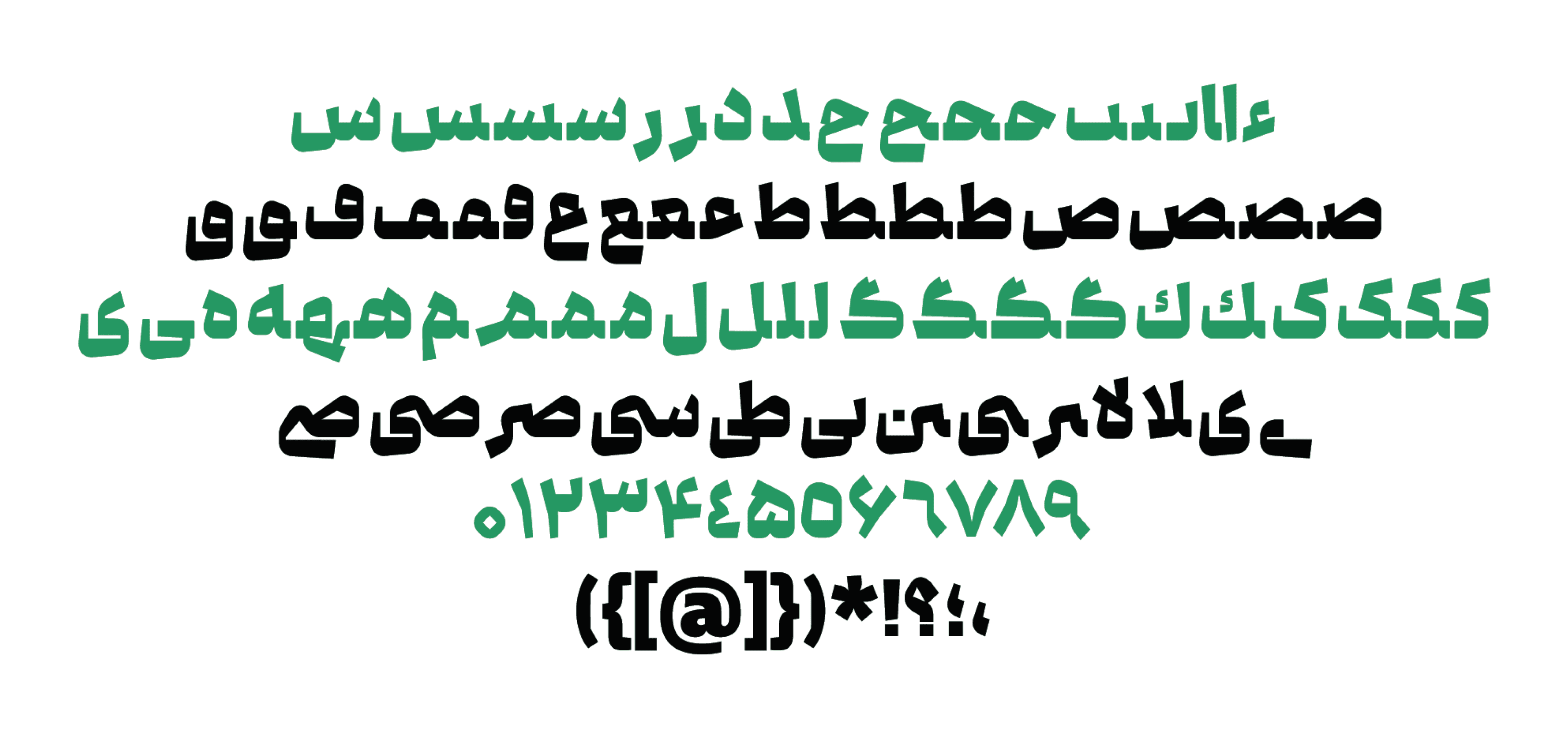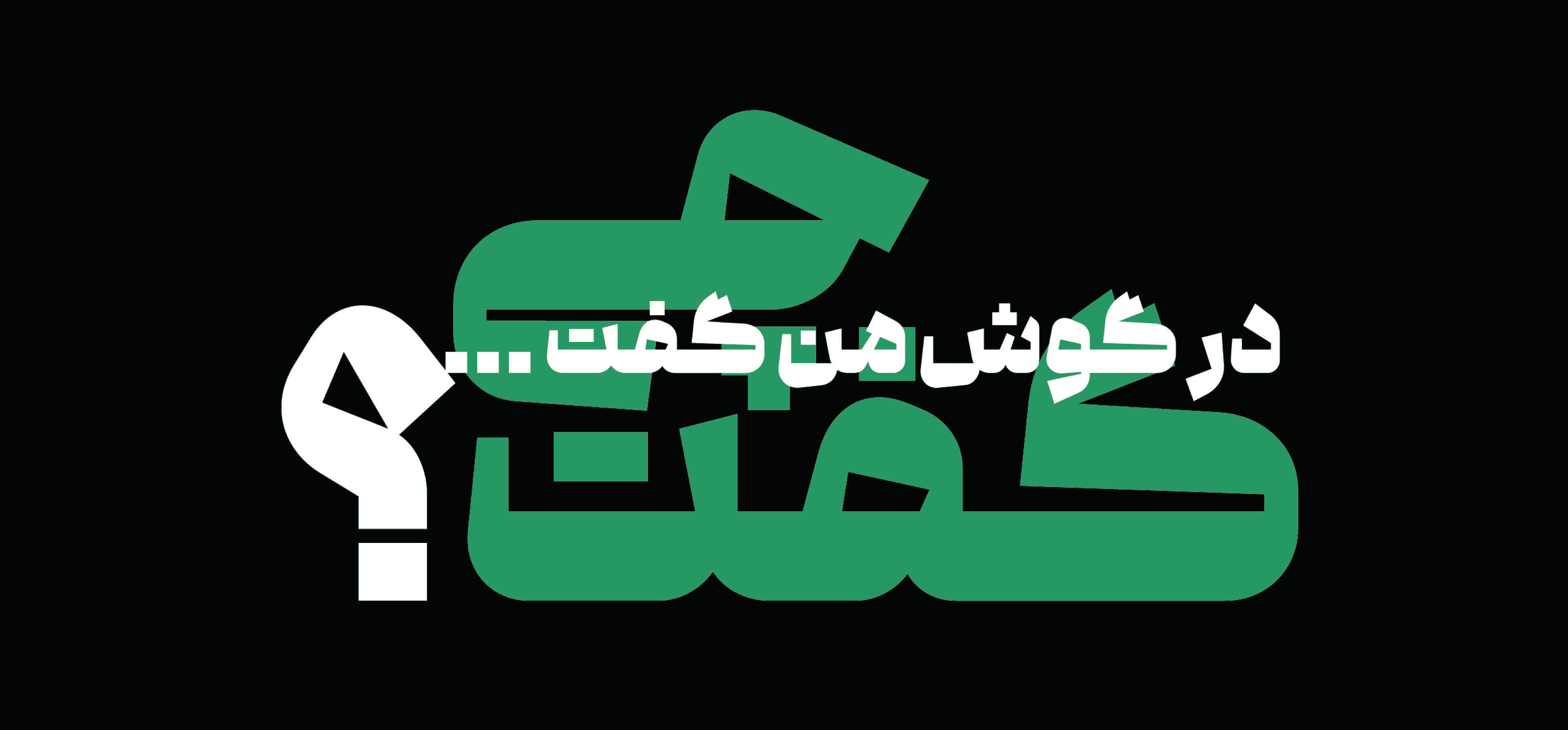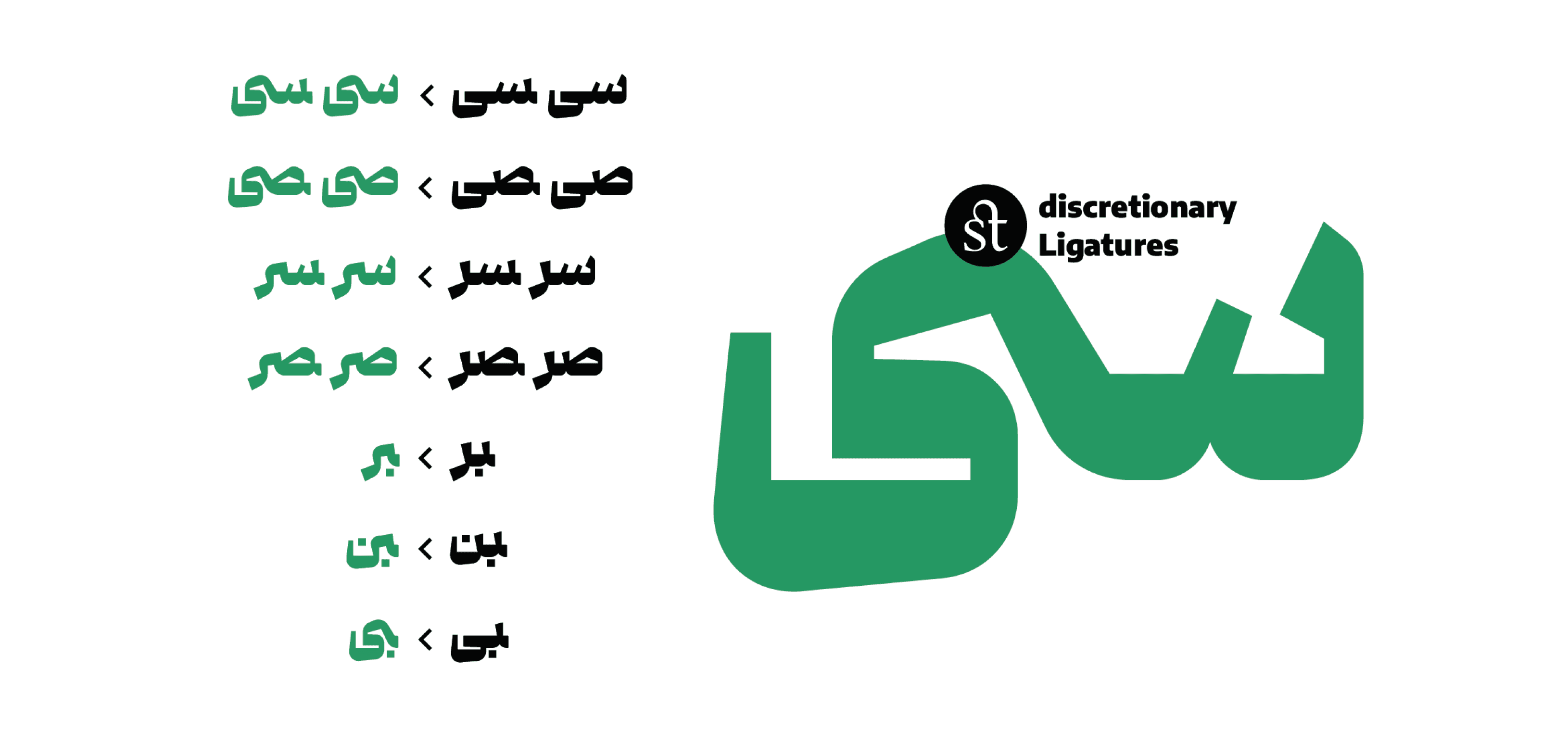
"گفته" هو خط عرضي ثقيل يتميّز بطابع فنّي واستعراضي. في حوالي عام 2019، تم رسم بعض الحروف يدويًا على الورق، وكانت تحمل طابعًا مميزًا وإحساسًا خاصًا. وبعد عام، تقرر تطوير تلك الحروف، لكن النتيجة لم تكن مرضية، فتم أرشفة المشروع. إلى أن جاء عام 2023، وبعد المشاركة في دورات الأستاذ دامون خانجانزاده، أُعيد العمل على المسودات من جديد، ومع تركيز أكبر على المفهوم وتصميم الحروف الأولى، وُلد خط "گفته" بصيغته النهائية.